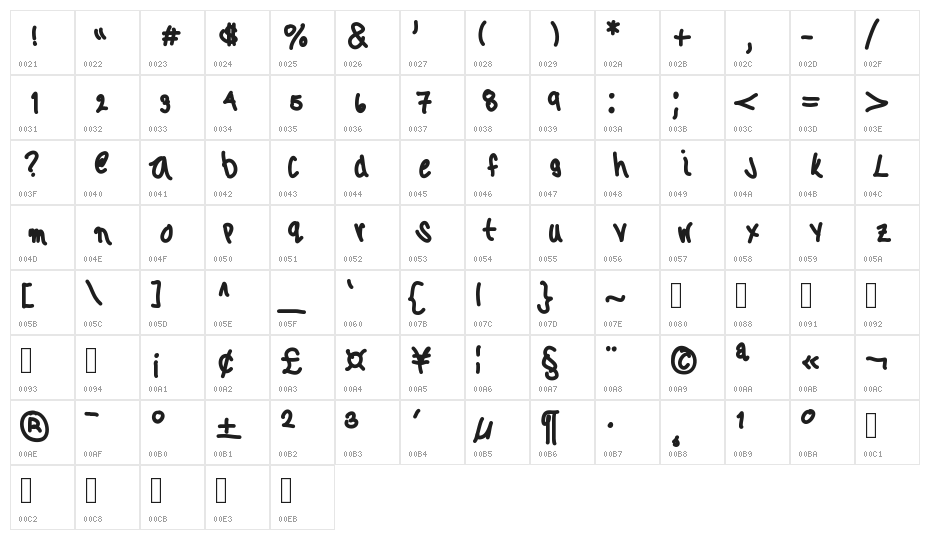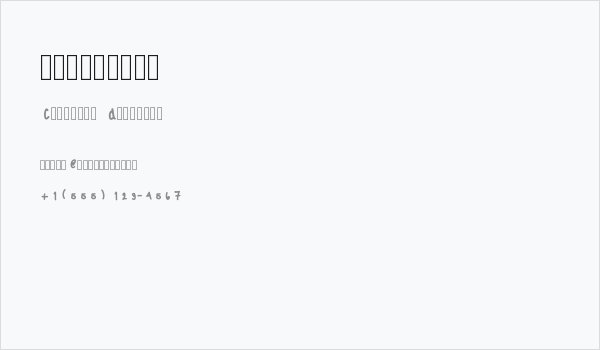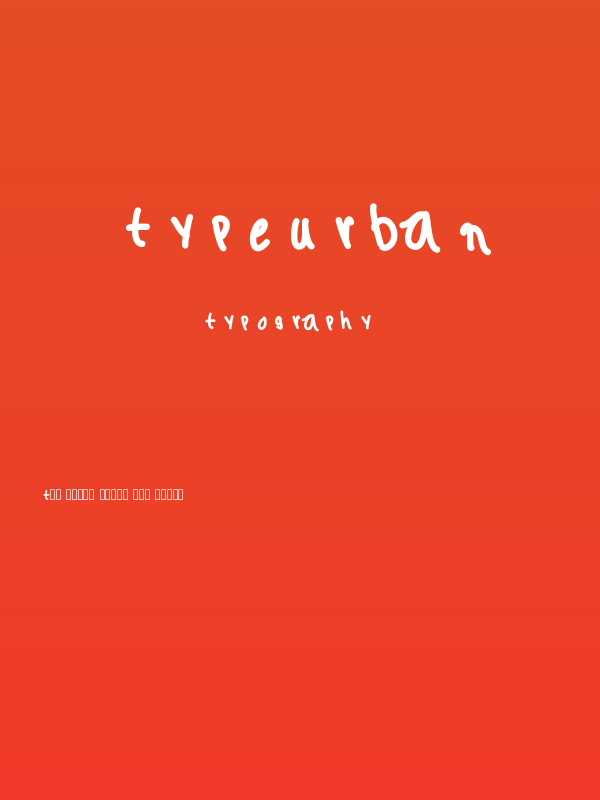
typeurban Font
| 整体风格 | Casual, Urban, Playful |
| 使用场景 | Headlines, Posters, Social Media Graphics |
| 推荐项目 | Ideal for projects that require a fun and informal touch, such as children's books, greeting cards, posters, and social media graphics. |